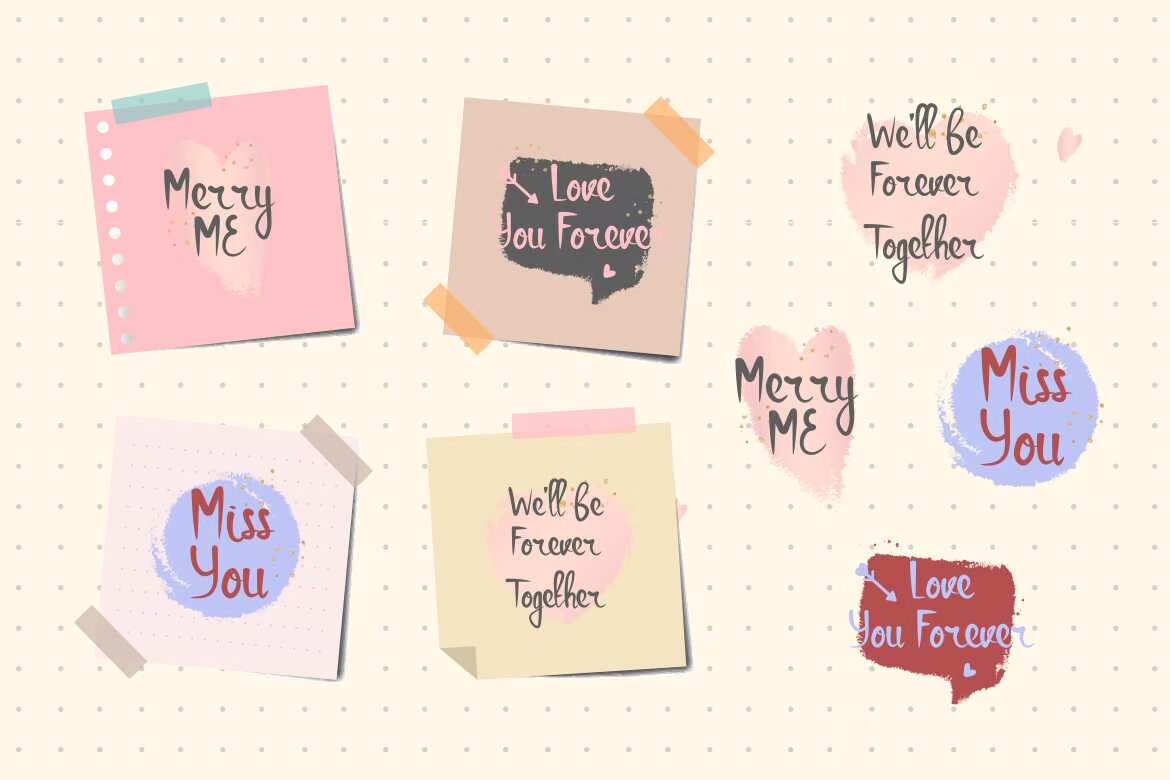
SaluyUISA和WritenScript字体。它是用于品牌和数字设计的Nauthentic Modern AlligraphyLookmaking完美版。SaluyUISA和WritenScript字体。它是用于品牌和数字设计的Nauthentic Modern AlligraphyLookmaking完美版。